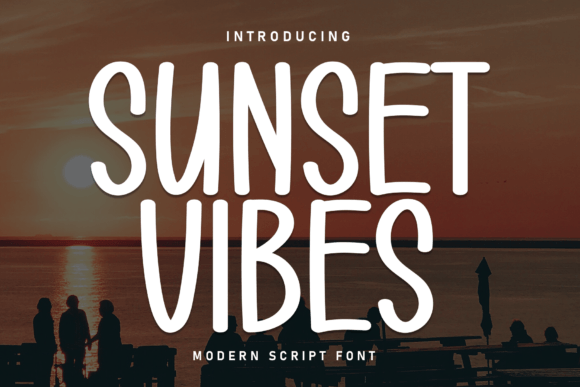
Sunset Vibes Font
استمتع بجمالية غروب الشمس مع Sunset Vibes Font، الخط الذي يجمع بين الأناقة والانسيابية ليمنح تصاميمك طابعًا عصريًا ومميزًا. يتميز هذا الخط بحروف ناعمة ومنحنية مستوحاة من أجواء الغروب الدافئة، مما يجعله مثاليًا لتصميم الشعارات، الدعوات، منشورات وسائل التواصل الاجتماعي، أغلفة الكتب، والمزيد!
مميزات الخط:
✔ تصميم فريد وجذاب يعكس إحساس الاسترخاء والإبداع
✔ يدعم الحروف الكبيرة والصغيرة لمرونة في الاستخدام
أطلق العنان لإبداعك مع Sunset Vibes Font واجعل تصاميمك تنبض بالحياة! ????✨